吟味された素材と丁寧な手仕事で国内外に熱心なファンを持ち、長年にわたって愛されているブランド『45R』を擁するフォーティファイブアールピーエムスタジオ株式会社(以下「45」)は、1977年の創業から45周年を迎えた2022年にWebサイトをリニューアルし、新たに「ブランドECサイト」と「コーポレートサイト」を設けました。
どちらのサイトにも、モリサワのWebフォントサービスTypeSquareから「A1ゴシック」と「A1明朝」を採用いただいています。
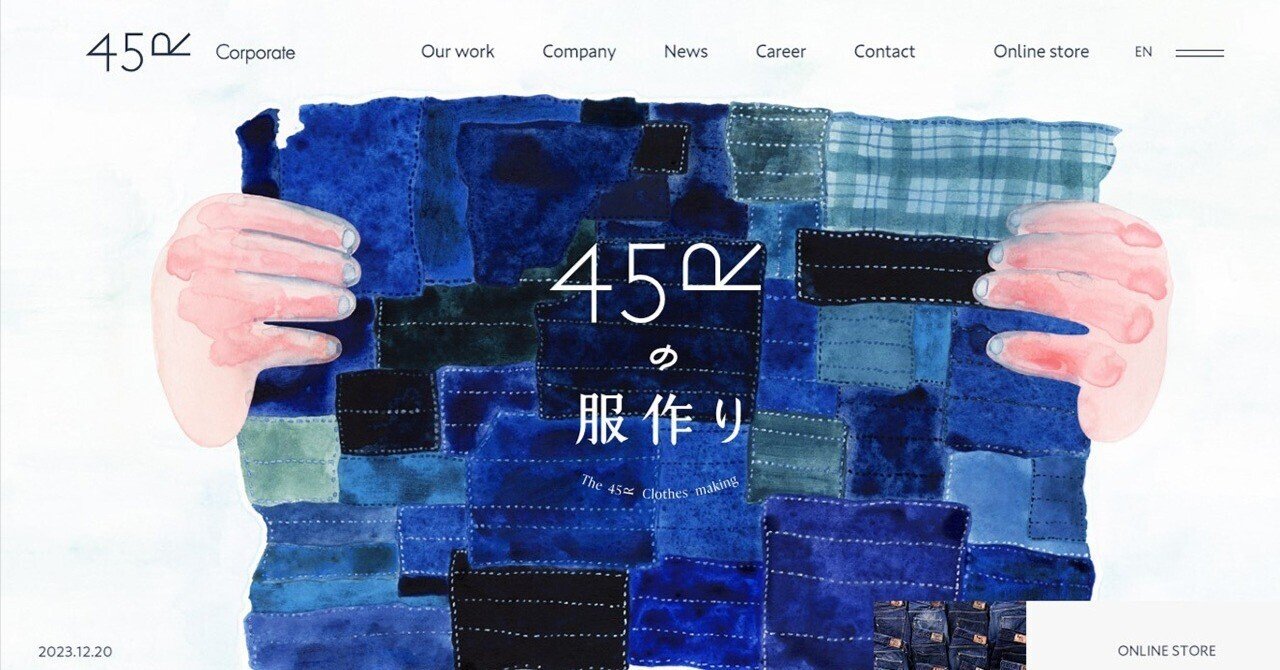
インタビューの内容で印象に残ったのは、それまではテキスト部分の文字をひとつひとつ画像化して表示しており、サイト更新のたびに画像を作り直して大変苦労されていたという点です。
「サイトのイメージづくり」と「更新しやすさ」の両立は、Webフォントを採用する大きなメリットのひとつです。
ブランドイメージに沿ったフォントで文章を表示しつつ、更新の際はテキスト部分を修正するだけで済むので、画像を作り直すといった手間がなく、大幅に工数を短縮できます。
画像化した文字は検索にも引っかからないので、SEO対策としても効果的です。
また、今回「A1」書体シリーズのフォントを採用いただきましたが、フォント選定の決め手は、もともと45が持っていたオリジナル欧文フォントとの相性がいいことに加え、「ヴィンテージの味わい」や「真心がのせられる」など、45が大切にしていることにマッチしているということでした。